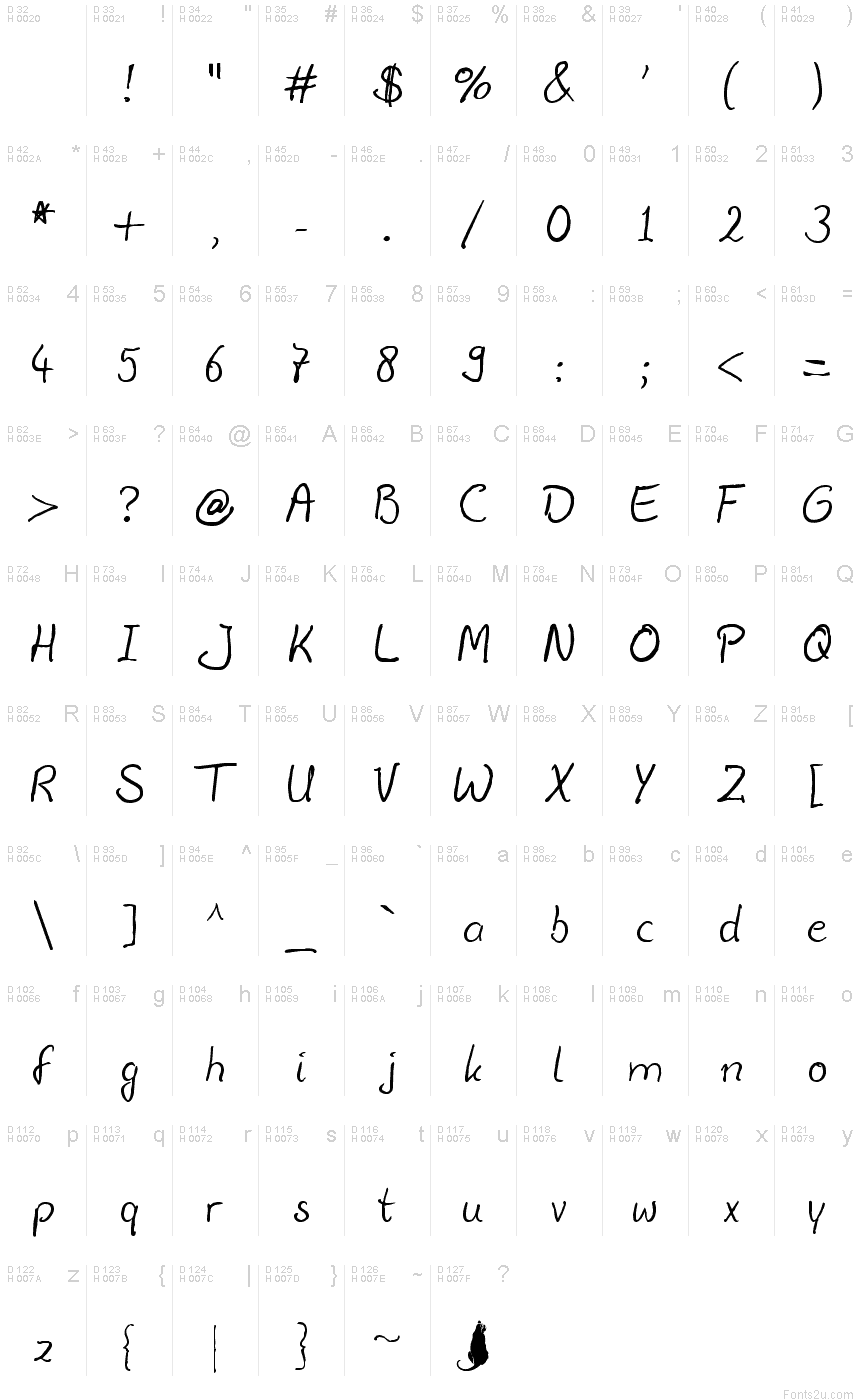
Julius B Thyssen
Julius B Thyssen من تصميم Julius Benedictus Thyssen هو خط مجاني مكتوب بخط اليد يجسد إحساس ضربات القلم السريعة والواثقة على الورق الأملس. تمنحه منحنياته اللطيفة، وحروفه المائلة قليلاً، وتباعده المريح إيقاعاً ودوداً وعفوياً يسهل قراءته مع الحفاظ على لمسة شخصية ساحرة تشبه الحبر. يبدو وكأنه ملاحظة أنيقة ومدروسة كتبها شخص حقيقي، بعيداً عن صرامة الخطوط الرسمية أو مبالغتها في التنسيق.
باستخدام Julius B Thyssen، يمكنك إضافة لمسة دافئة إلى الدعوات، وبطاقات المعايدة، والعلامات التجارية الشخصية، وتغليف المنتجات، واقتباسات وسائل التواصل الاجتماعي، أو المخططات الرقمية. يتألق هذا الخط المجاني عند استخدامه بأحجام كبيرة، حيث يمكن للاضطرابات الطفيفة والأشكال المنحنية أن تتنفس بوضوح. أقرنه بخط هندسي بلا زوائد (Sans-serif) نظيف للنص الأساسي للحفاظ على توازن التنسيق، واترك النمط اليدوي يضفي طابعه على العناوين والأسماء والعبارات القصيرة التي تحتاج إلى لمسة إنسانية.